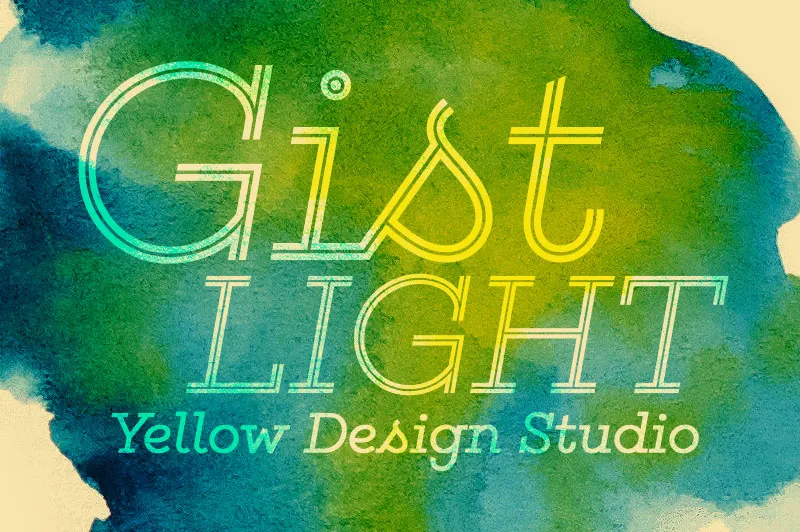
Esta fonte ‘Gist Light Font’ é uma ótima escolha para dar um toque vintage e moderno ao seu design. Ela vem do Hamilton designer, e sua aparência casual e leve agradou muitos criativos por igual. Este slab serif está disponível em versão completa da Yellow Design Studio e é perfeito para aqueles que desejam adicionar esse estilo retro à suas criações sem comprometer o conforto de leitura. Se você está procurando por uma fonte casual, elegante e leve, ‘Gist Light Font’ provavelmente vai se tornar um favorito. Descarregue-a agora e experimente essa incrível combinação de estilo clássico e modernidade!